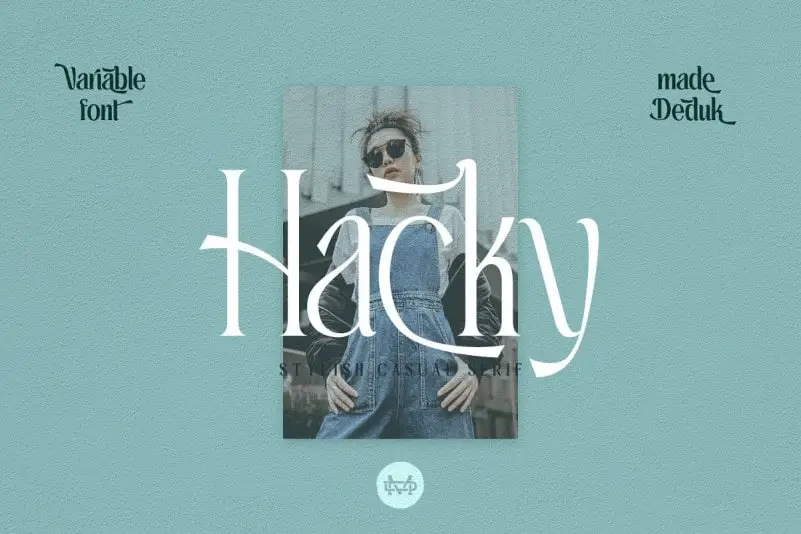
Hacky Serif Font – Download Grátis
A Hacky Serif Font é uma família elegante de serif que se inspira no famoso logotipo minimalista moderno. Inspirada pela simplicidade e sofisticação do design contemporâneo, esta fonte foi criada pelo designer madeDeduk e é perfeita para projetos como templates, brochuras ou qualquer outro tipo de material gráfico. Com seus ângulos suaves e 9 pesos variáveis, a Hacky Serif oferece um amplo leque de opções alternativas. Suave e minimalista, esta família de fontes cria uma aparência clara e sóbria, sem apelos exagerados para qualquer projeto de branding ou arte digital. Seja para criar logotipos, embalagens de produtos, convites, estampas, etiquetas, cartazes ou até mesmo camisetas personalizadas, a Hacky Serif está pronta para transformar suas ideias em projetos cheios de estilo e precisão.